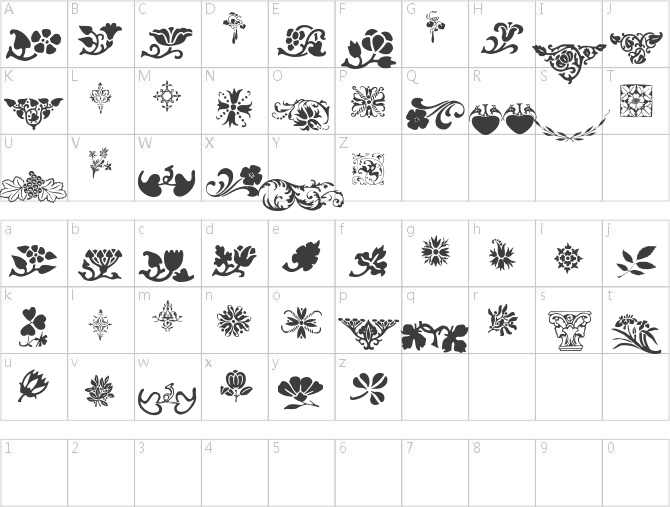
Printers-Ornaments-One 詳情頁
Printers-Ornaments-One字體字庫是一款讓人賞心悅目、百看不厭的英文字體,適合各類廣告和產(chǎn)品包裝設(shè)計(jì)應(yīng)用,字體大小0.08MB,格式為ttf字體,上傳用戶是小籃子,作者/版權(quán)方為未知